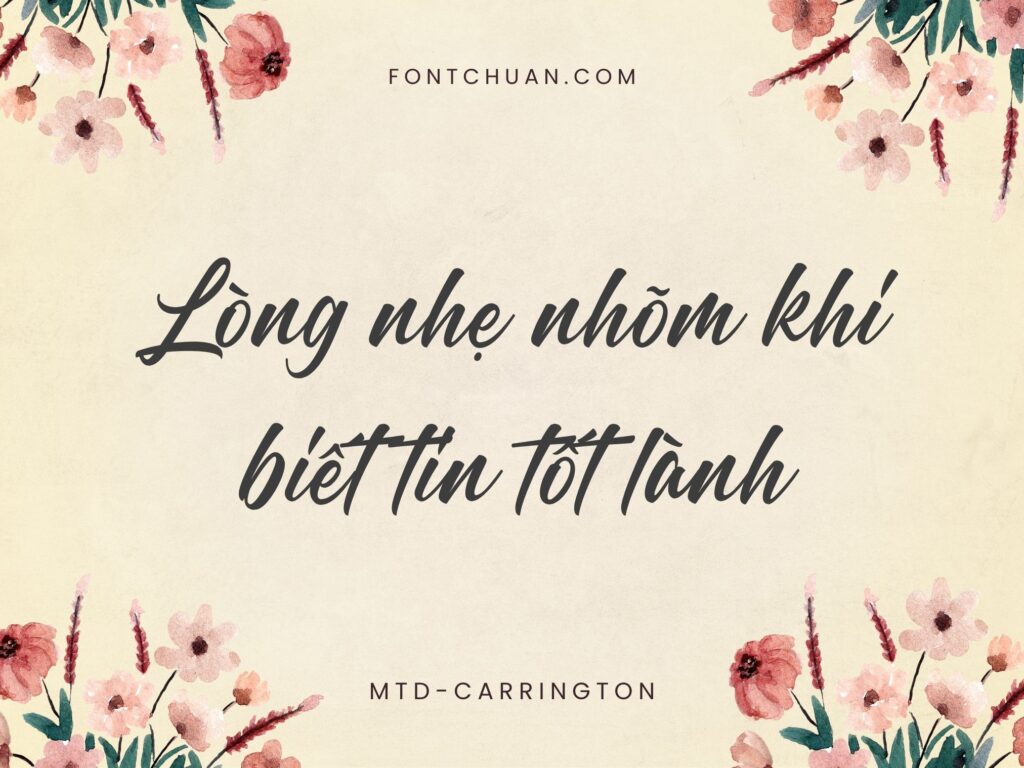
Font MTD Carrington Việt Hóa
Font MTD Carrington là một kiểu chữ viết tay mang phong cách calligraphy, được thiết kế bởi Nugs Studio và đã được Việt hóa bởi Mộc Hạ. Font này hỗ trợ đầy đủ tiếng Việt cùng hơn 90 ngôn ngữ khác, mở rộng khả năng ứng dụng trong các thiết kế đa ngôn ngữ. Đây là một trong những phông chữ được cộng đồng thiết kế đánh giá cao và sử dụng trong nhiều dự án sáng tạo, đáp ứng nhu cầu đa dạng của người dùng.
MTD Carrington nổi bật với các đường nét mềm mại và uyển chuyển, tạo cảm giác thanh lịch và nghệ thuật. Font rất phù hợp cho các thiết kế logo, tiêu đề, bao bì sản phẩm, thiệp mời và các ấn phẩm đòi hỏi sự tinh tế và độc đáo. Các ngành nghề phù hợp bao gồm quảng cáo, giáo dục, công nghệ, thiệp cưới và ảnh cưới. Font này cũng lý tưởng cho các sự kiện như Tết, Giáng sinh, Valentine và các lễ hội khác.